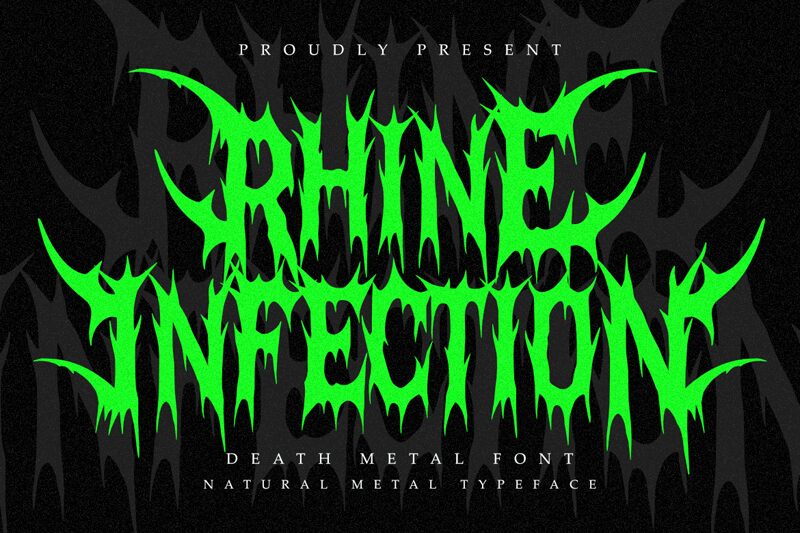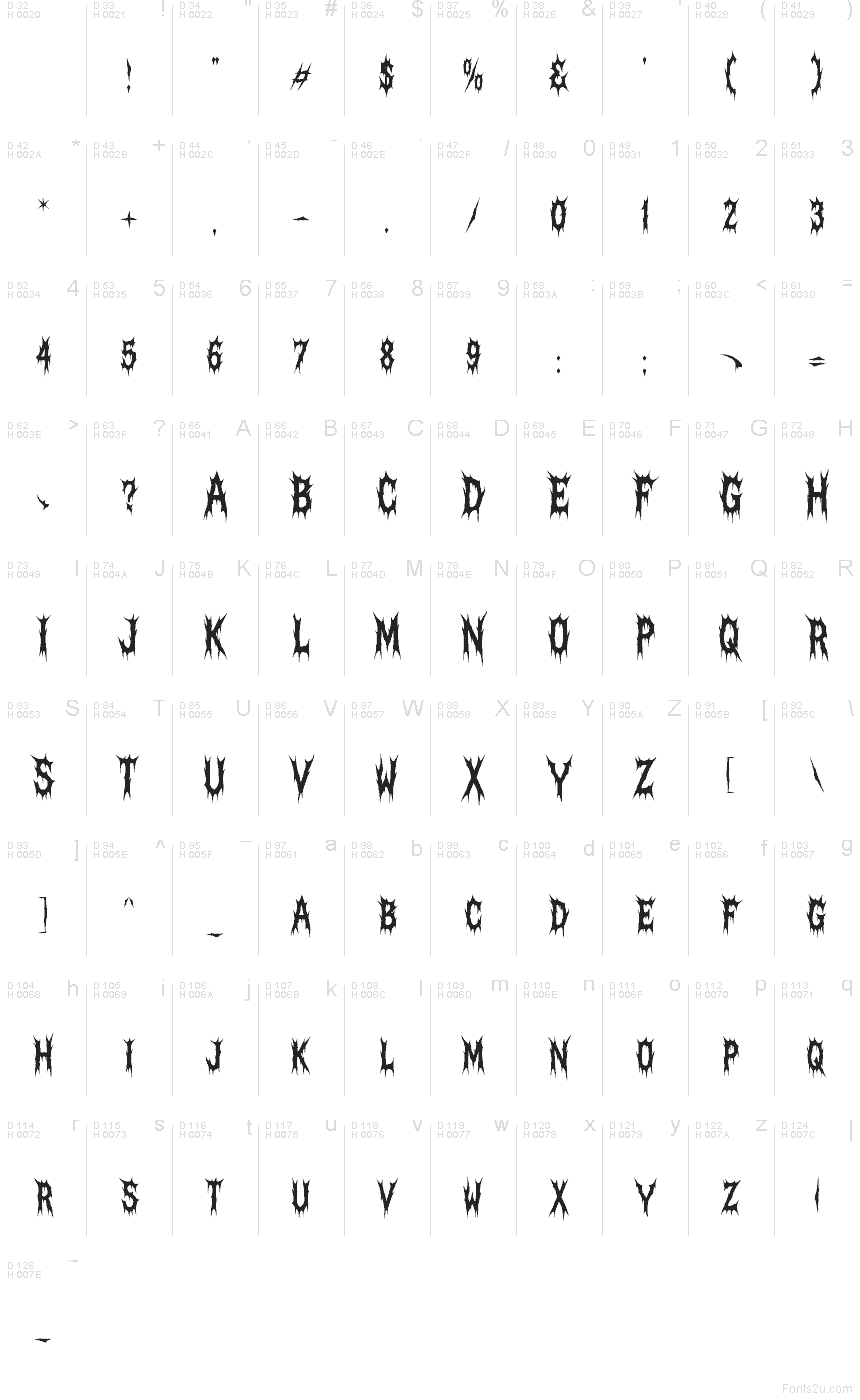
Rhine Infection od Masyafi Studio je bezplatné gotické písmo s potrhanými, zubatými tvary a ostrými hroty, které vyčnívají z každého písmene. Nepravidelné řezy mu dodávají ponurý, „nakažený“ vzhled, aniž by však utrpěla základní struktura znaků.
Rhine Infection skvěle funguje na hororových plakátech, metalových logách, halloweenských letácích, názvech her, obalech alb a grafice temných akcí. Jeho drsný, roztříštěný styl má dostatek charakteru pro krátké nápisy, obnošené etikety a dramatické přebaly, kde písmo musí působit nepřátelsky a napjatě.